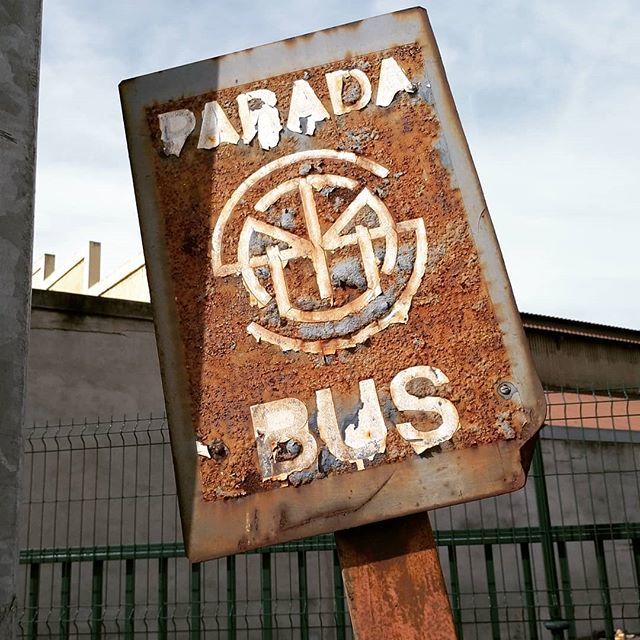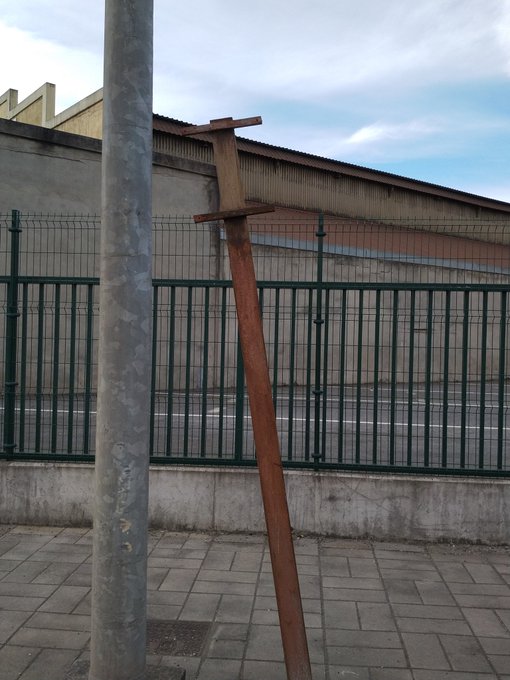
Placa Parada del SMTU
Hace prácticamente un año que se publicó en Instagram esta imagen. Se trata de pequeña placa que indicaba donde estaba ubicada una parada de bus en Nueva Montaña, junto a la entrada de la Fábrica. La placa estaba totalmente oxidada, pero aún se veía el monograma tan característico que identificaba a los antiguos autobuses.
Marzo 2019. Foto: Santatipo
La Historia de la empresa municipal de Transportes Urbanos de Santander (TUS) se remonta hasta finales del siglo XIX. Es e 1961 cuanto adquiere la denominicación de «Servicio Municipalizado de Transportes Urbanos»(1), que posteriormente pasaria a ser «Servicio Municipal de Transportes Urbanos de Santander» con el monograma tan icónico, hasta 2006 donde pasa a denorminarse como TUS. Por ello, es problable que la placa sea de los años 80.
La historia podría quedar aquí, pero resulta que unos meses después pasando por el mismo sitio, me doy cuenta de que la placa ya no está:
Enero, 2020. Foto: Santatipo.
A raiz de ello, se lanzó el aviso en twitter y el resto ya es historia. Se descubrió que apareció en un Bar como elemento decorativo; aquí tenéis el Hilo.
Con esto, desde el proyecto, queremos poner el acento en que muchas veces los elementos gráficos (Placas, Carteles o Rótulos) son desmontados o bien para decorar como es este caso, o para su venta. Como todo material patrimonial, cuando esto ocurre, se le saca de su contexto y sobre todo la ciudad pierde una parte importante de su historia local; además de que la calle pierde parte de su identidad y memoria. Desde la Red en Defensa del Patrimonio Gráfico, pedimos que sean preservardos, dado que son parte intríseca de la ciudades.